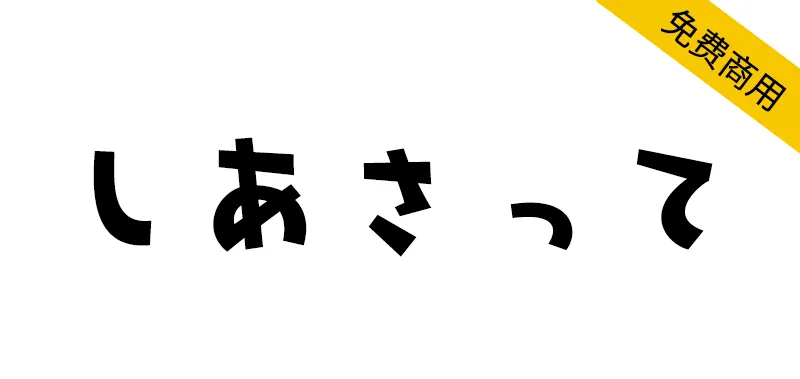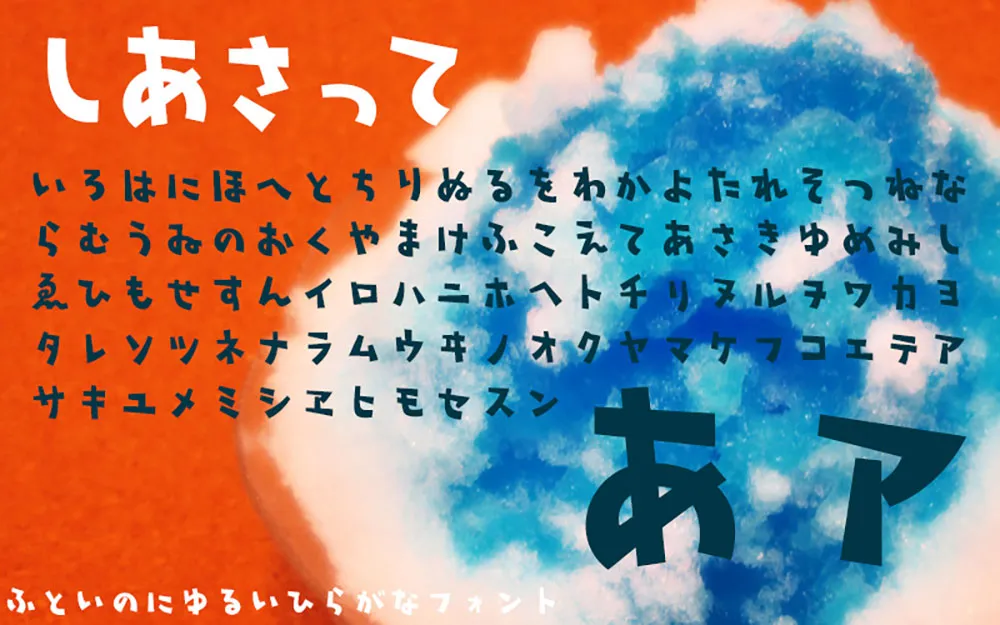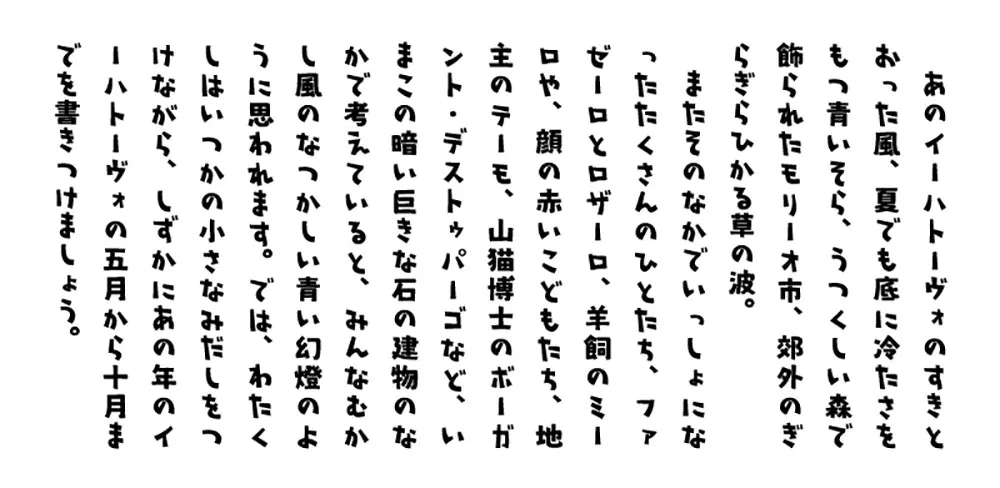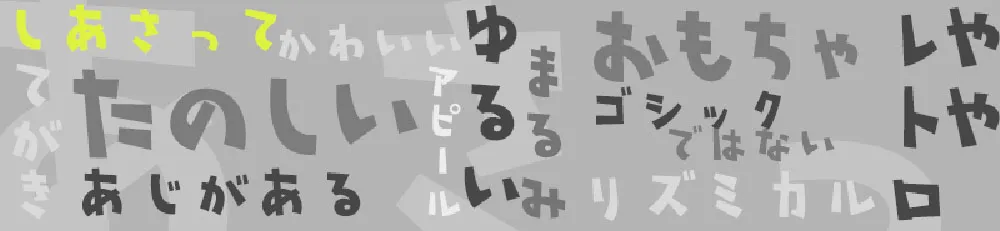
繼“ ひずみんかな ”之後,我的目標是手寫哥特式字體,它不是あさって,而是以あさって為原型,因此得名。它有著恰到好處的寬鬆感,讓人感覺很放鬆,而且還帶有幾分復古的感覺。這是僅適用於平假名和片假名的字體。
『ひずみんかな』に続いて手書きの形でゴシック體を目指したら、明後日どころか明明後日(しあさって)の方向にできあがったのでこんな名前。やる気がありそうでなさそうな程良いゆるさと、どことなくレトロ感も。ひらがな・カタカナのみのフォントです。